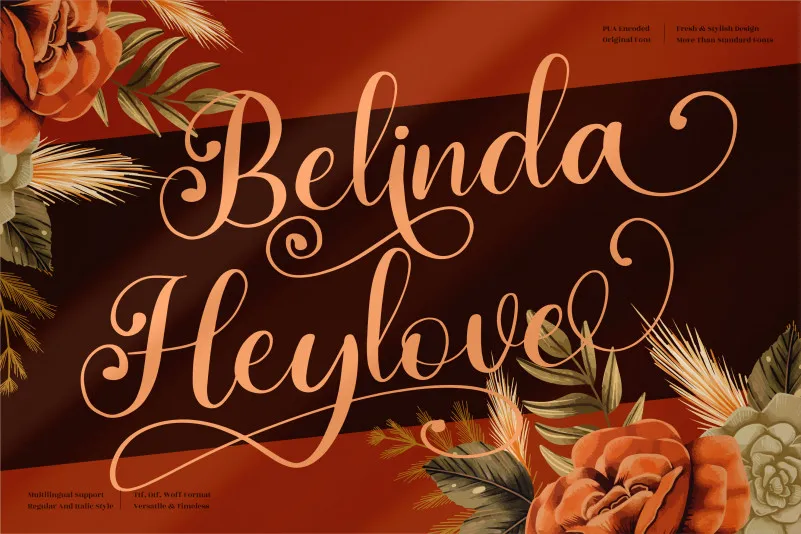
Belinda Heylove Font – Download Grátis
Belinda Heylove é uma fonte de calligrafia romântica projetada para satisfazer as necessidades de design variadas do seu projeto. Com sua delicadeza e elegância, ela pode ser usada em uma ampla gama de projetos incluindo logomarcas, embalagens de produtos, tags, cartões de lembrança, capas de livros e até mesmo enfeites para fotografias. Belinda Heylove oferece uma expressão única que tornará seus projetos elegantes e autênticos. Para quem procura um toque especial em design gráfico, esta fonte não pode ser esquecida. Ideal para designers, freelancers ou qualquer pessoa interessada em adicionar um elemento de sofisticação à sua marca ou projeto pessoal. Seja qual seja seu próximo projeto, Belinda Heylove está aqui para iluminá-lo com seu encanto único.